Mở đầu về tips là câu hỏi vô cùng quen thuộc mà các bạn newbie (nugu) vẫn thường hỏi tớ. Đó là LÀM THẾ NÀO ĐỂ CHỌN FONT HỢP ART? Vậy nên hôm nay tớ sẽ chia sẻ những kinh nghiệm cũng như cách chọn của tớ cho các cậu nhé!
1. Chọn font theo thể loại.
Thế nào là "chọn font theo thể loại"? Chọn font theo thể loại tức là tùy vào cái thể loại của cậu edit, tùy vào sự phù hợp với thể loại đó mà chọn font thôi. Hơi khó hiểu đúng không @@? Vậy thì cậu hiểu đơn giản là thế này.
Ví dụ cậu chọn thể loại tình cảm, nhẹ nhàng, thì font sẽ dạng uốn lượn, bay bổng, nói chung là dạng mềm.
Thể loại đáng yêu, hài hước thì dùng font cũng "đáng iu".
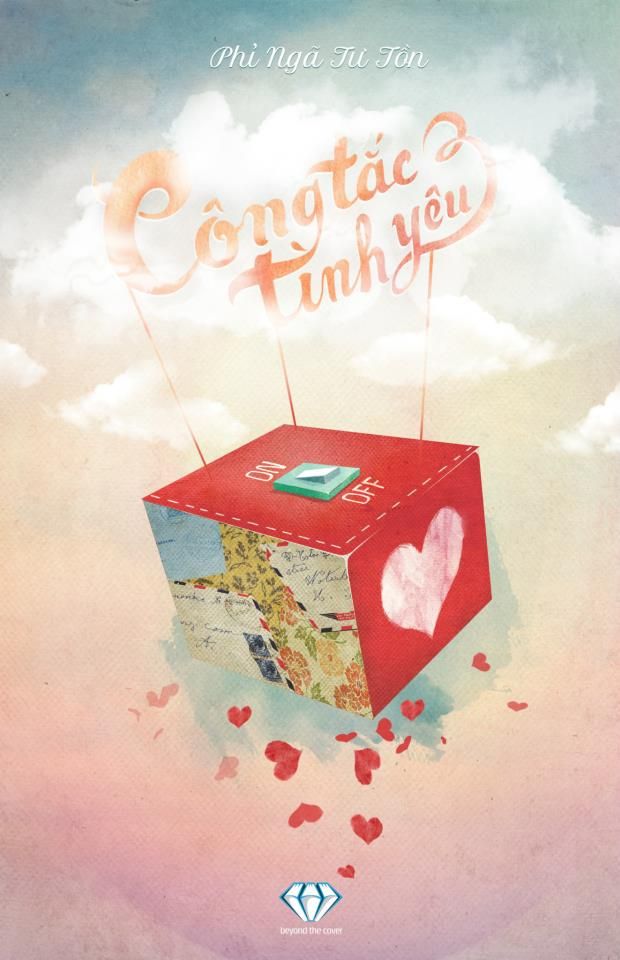
Thể loại hành động thì chọn font cứng, không quá hoa mỹ mà siêuuuu đơn giản.
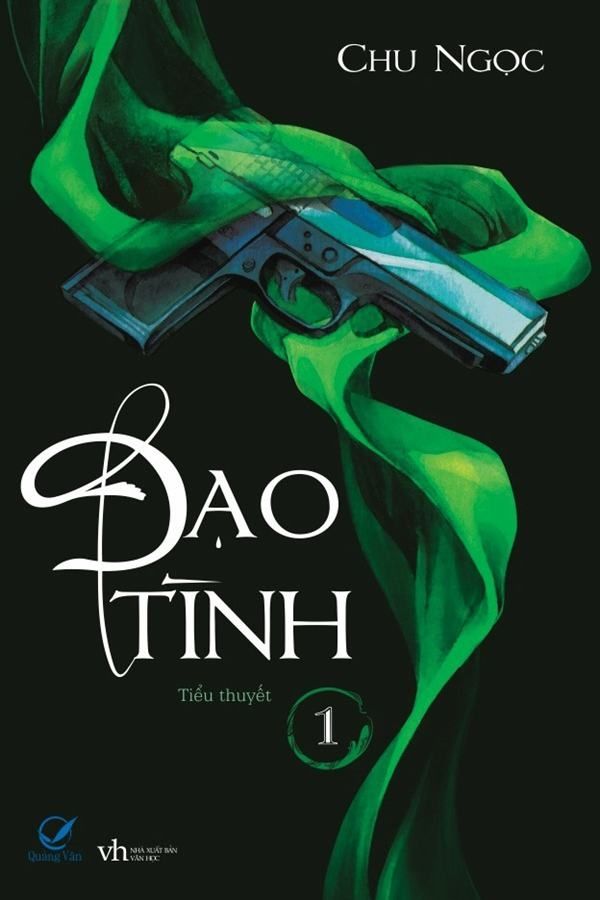
Thể loại kinh dị, bí ẩn thì chọn font thư pháp, hoặc font ma mị (?) hay là các font nhìn lạ mắt.
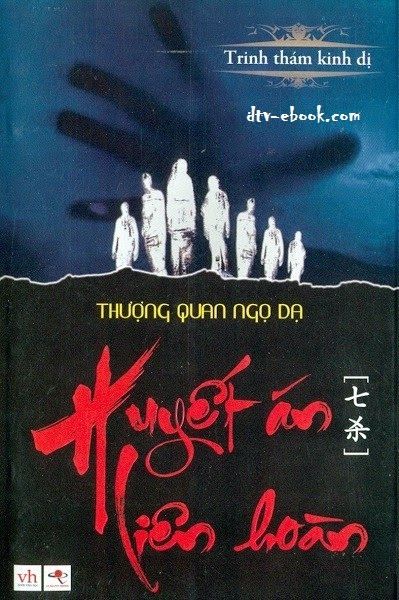
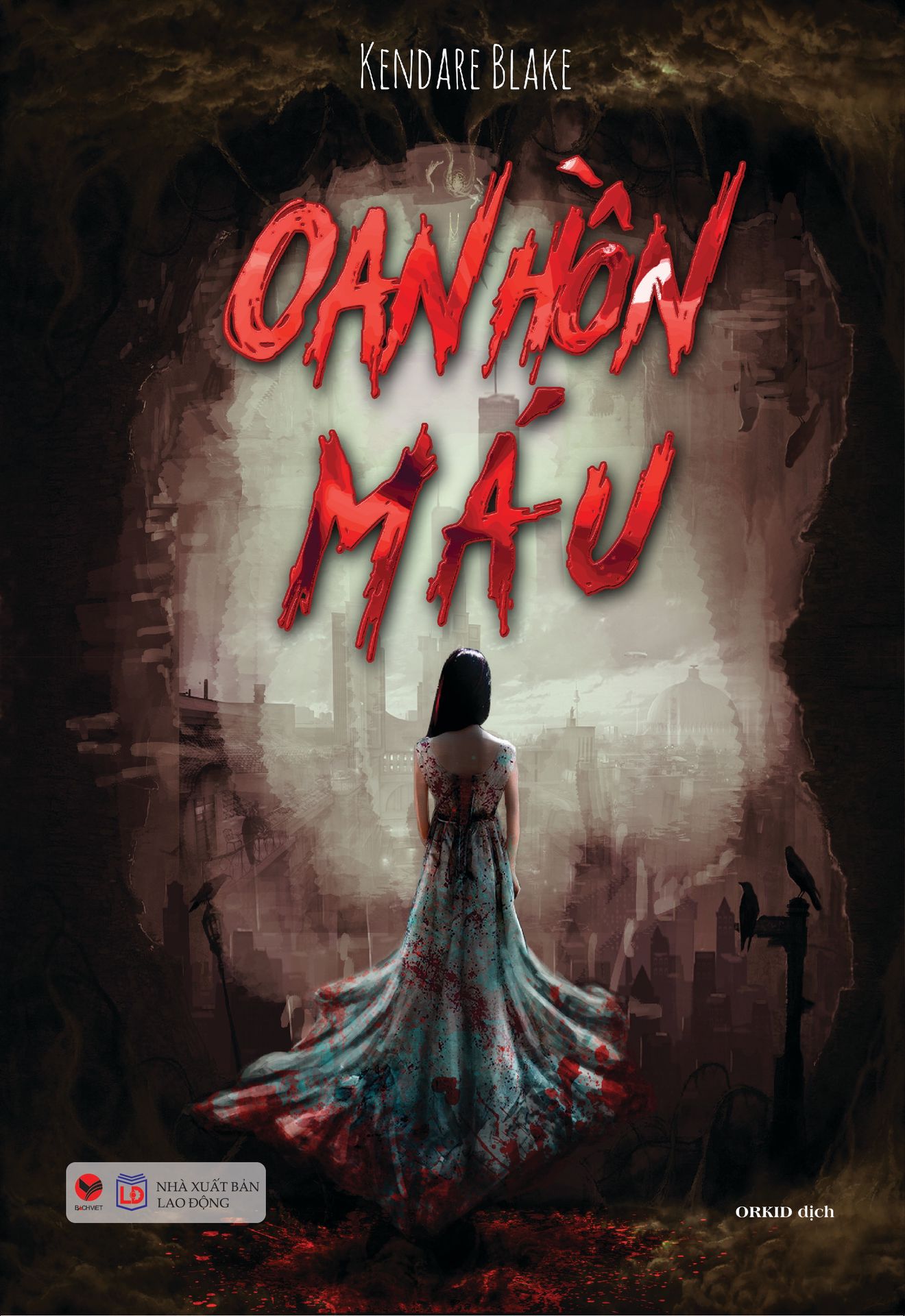
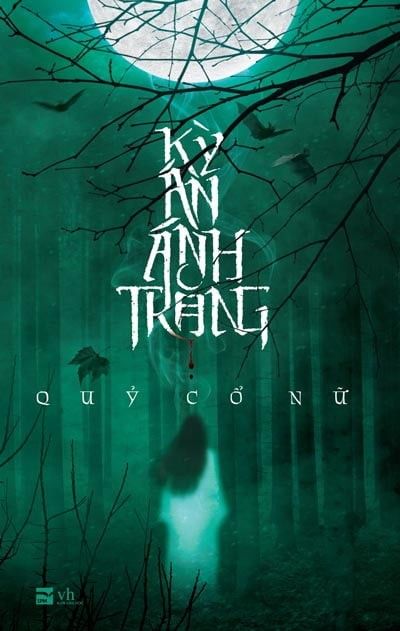
Thể loại cổ trang, đương nhiên là dùng font thư pháp, cổ trang, hoặc là font Romaji như dưới.
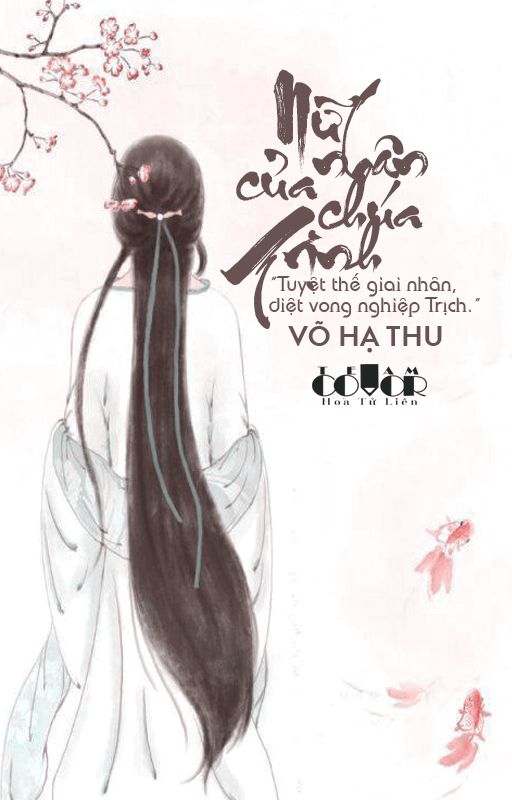
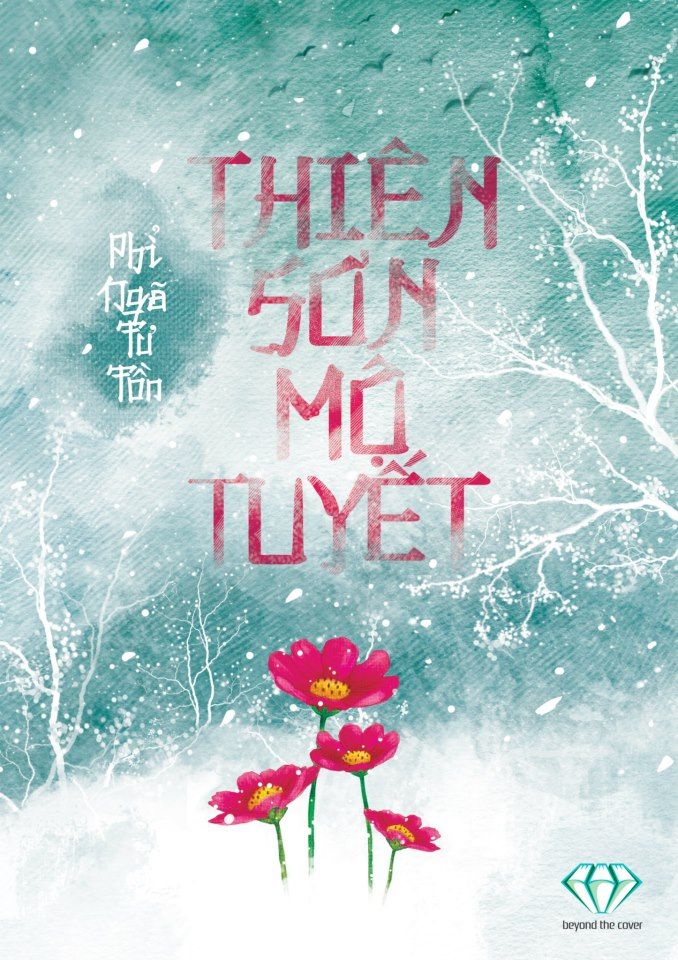
Còn rất nhiều thể loại, nhưng mà tớ chỉ ví dụ sơ qua mấy cái trên thôi nhé @@
Đó là thể loại của bookcover, vậy rộng hơn bookcover còn bao nhiêu thể loại khác nữa, làm thế nào để chọn font?
Các thể loại khác, cụ thể như quotes cover, scrapbook, graphic, banner,... thì nên chọn font kiểu gì? Chắc hẳn cậu đã từng rất băn khoăn phải không? Vậy giờ thử điểm qua vài cách của tớ nhé!
Về thể loại scrapbook, tớ thường chọn font mập mạp, mũm mĩm :> vì font đó tạo nên sự đáng iu đó!!! Scrapbook thường là những art chimte mà ~
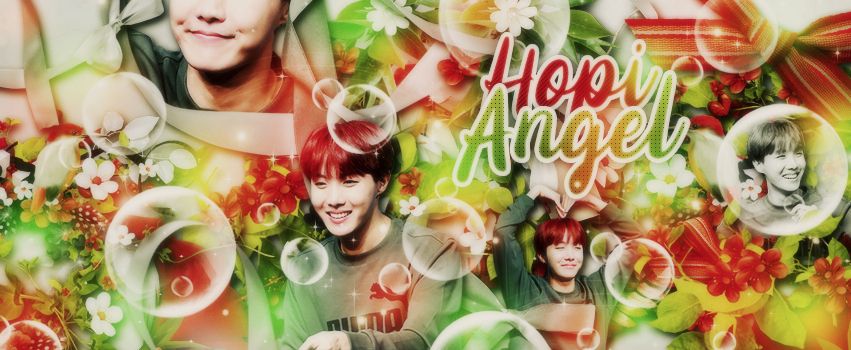
Về thể loại quotes cover, tớ hay dùng các font mềm, đặc biệt là font uốn lượn, font handwriting.
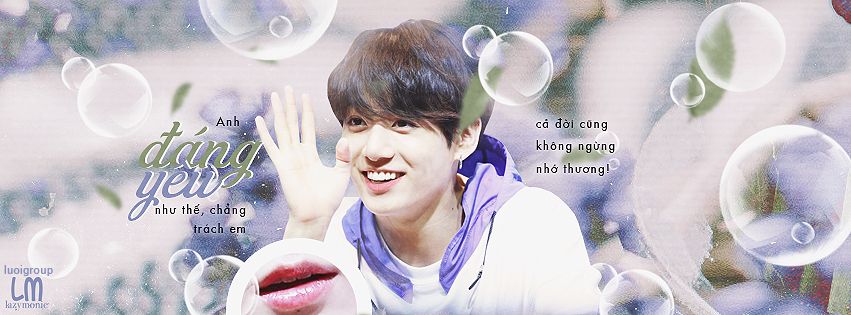
Về graphic, tớ chọn các font cứng, thật sự thì tớ chỉ làm mỗi simple nên toàn dùng font cứng không chân, mấy font điển hình là Tahoma và Arial ~ hoặc các font na ná vậy ý. Còn các font dành cho graphic mix tùm lum tùm la texture, nói chung là dạng try hard ~ thì tớ tham khảo họ hay dùng font cứng, nhưng có chân hoặc các font nhìn lạ lạ ý.
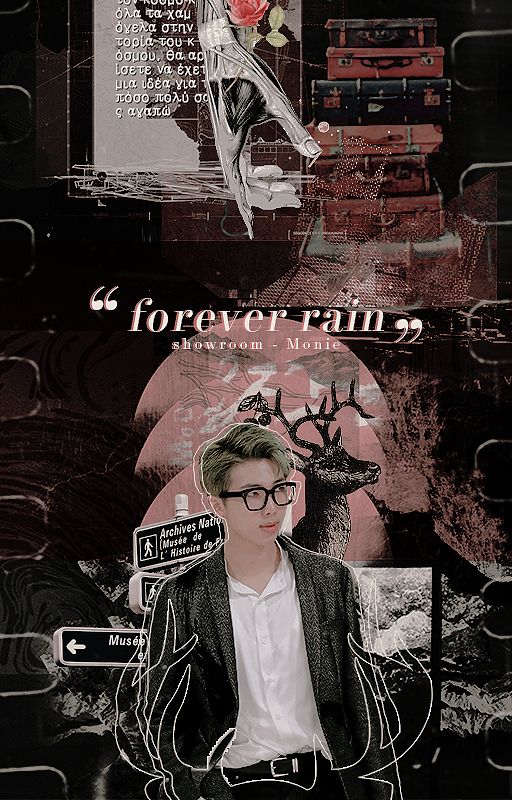
2. Chọn font theo tone màu của art.
Theo tone màu của art? Nghe thì lạ đấy, nhưng thực sự Monie rất hay áp dụng cái này luôn ~~
Vậy thì bí quyết là gì?
Ez thôi, đó là các art tone màu sáng, như hường phứn, xanh bạc hà, cam nhẹ, nói chung là các màu nhẹ :> thì dùng font mềm uốn lượn nè, art tone màu tối thì sài font handwriting dày mềm.
3. Chọn font theo "cảm hứng, sở thích".
Lại bảo là chưa bao giờ cậu gặp trường hợp là rất rất rấtttttt thích một font này, nhưng lại luôn dập khuôn là "cái này dùng font cứng, cái này dùng font mềm" blabla ~~ nên không dám dùng trong art cậu đang làm đi. Tớ cũng vậy thôi, nhưng mà tớ đã thử dùng font theo sở thích của tớ và bùmmm, siêu ư là xinh luôn ~ (nghe giống tự luyến nhở? @@)
Vậy nên, nếu cậu thích một font nào đó, hãy cứ dùng nó cho art của mình. Ơ nhưng nếu mà nhìn nó quá không hợp @@ thì chắc chắn phải đổi chứ cũng đừng tự cố thuyết phục là vì mình thích nên mình dùng nhé! Ý của tớ nói là hãy thử nó thay vì chỉ tự hỏi liệu nó có đẹp không ý @@ Vẫn nên nhớ một số thể loại vẫn luôn có điều cấm kỵ trong cách chọn font thuộc thể loại đó đó nha.